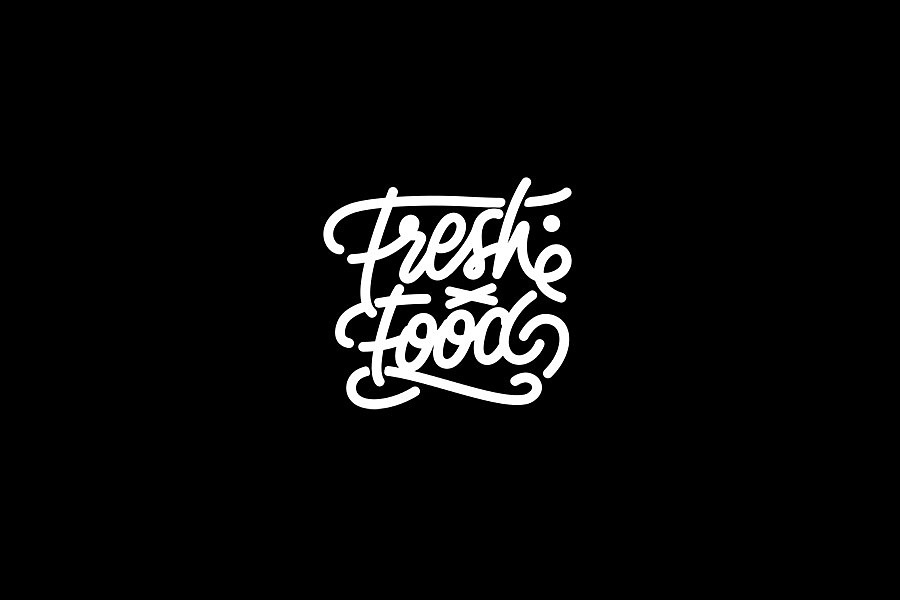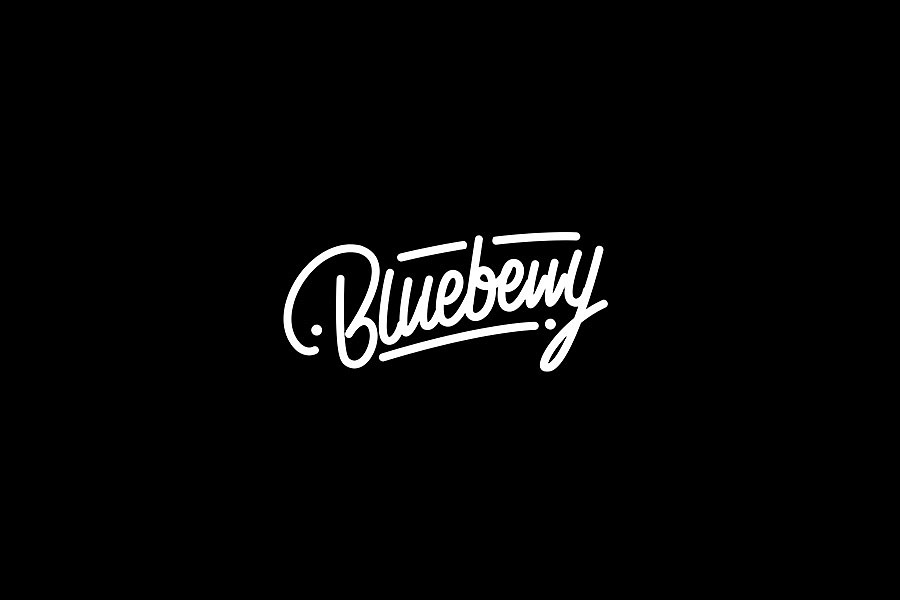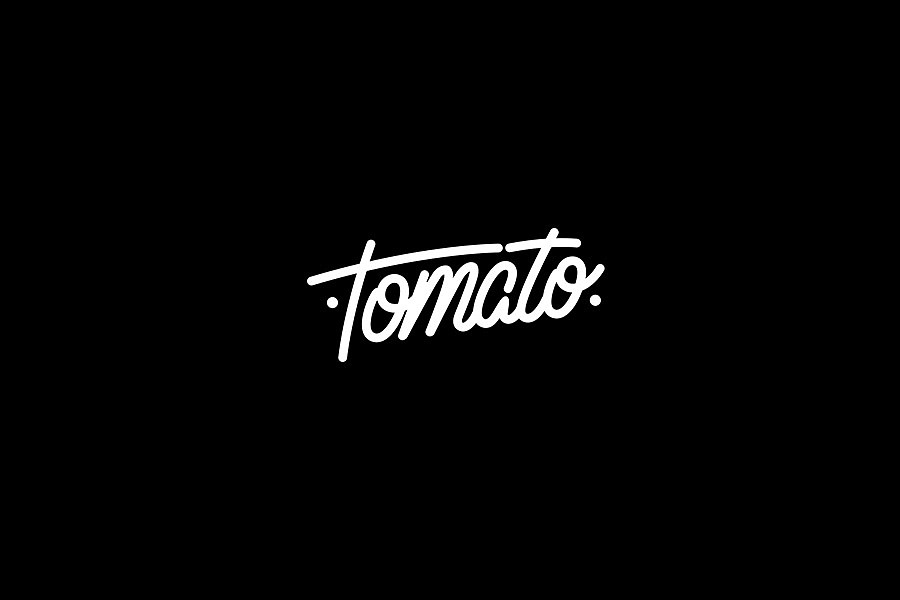
赶在过年前来一发
16年是不断学习的一年,从开始了解手写英文字体到不断尝试练习,鬼知道都经历了些什么~
上半年发的一些练习没想到受到了很多人的喜欢,是意外的收获!
但是这其中也有很多不足,同时学习太多的字体导致很多都是徒有其表
所以下半年稍稍改变了下方向,每次只针对一种字形来研究学习,希望大家喜欢
针对这次的手写英文字,本来是想看看有没有可能做成字库的,但是发现每个组合的可能都千差万变